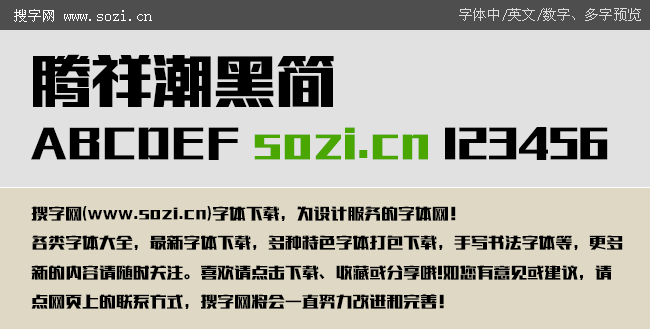
騰祥潮黑簡
搜字網(wǎng)提供一款騰祥潮黑簡中文藝術(shù)字體下載,騰祥潮黑簡字形結(jié)構(gòu)扁方、端莊,橫豎筆畫粗細比例適度、豎筆粗壯有力,布白均勻、行文貫通。整體筆畫看起來既粗壯醒目又清晰易讀。適合標題用字,可用于印刷出版、包裝設(shè)計、廣告設(shè)計、網(wǎng)頁設(shè)計等。